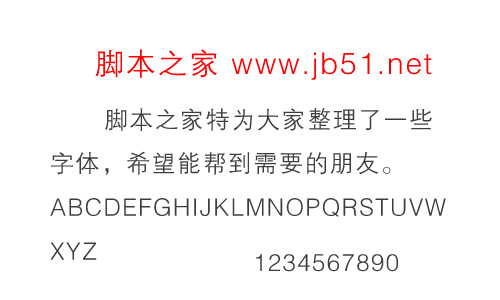
方正中等線簡(jiǎn)體字體是方正字體庫(kù)中的一種字體,方正等線體源自鉛字時(shí)代的黑體設(shè)計(jì)手稿。其字形風(fēng)格比較傳統(tǒng),中宮緊湊,筆畫兩端保留有喇叭口,撇捺筆畫弧度較大,富有書寫意味。方正等線體家族包含3款字重,曾被作為微軟公司W(wǎng)indows 8的系統(tǒng)默認(rèn)字體,其中方正中等線在Windows Phone簡(jiǎn)體中文界面下對(duì)應(yīng)的是“方正等線 Bold”。方正粗等線于2012年開發(fā)完成,是方正等線體家族中筆畫最粗的一款。方正等線體的字形樸素端正,清晰易讀,人文氣息濃厚,既適用于傳統(tǒng)印刷媒介的標(biāo)題與正文,又適用于屏幕閱讀。喜歡的朋友們可以前來(lái)下載使用。